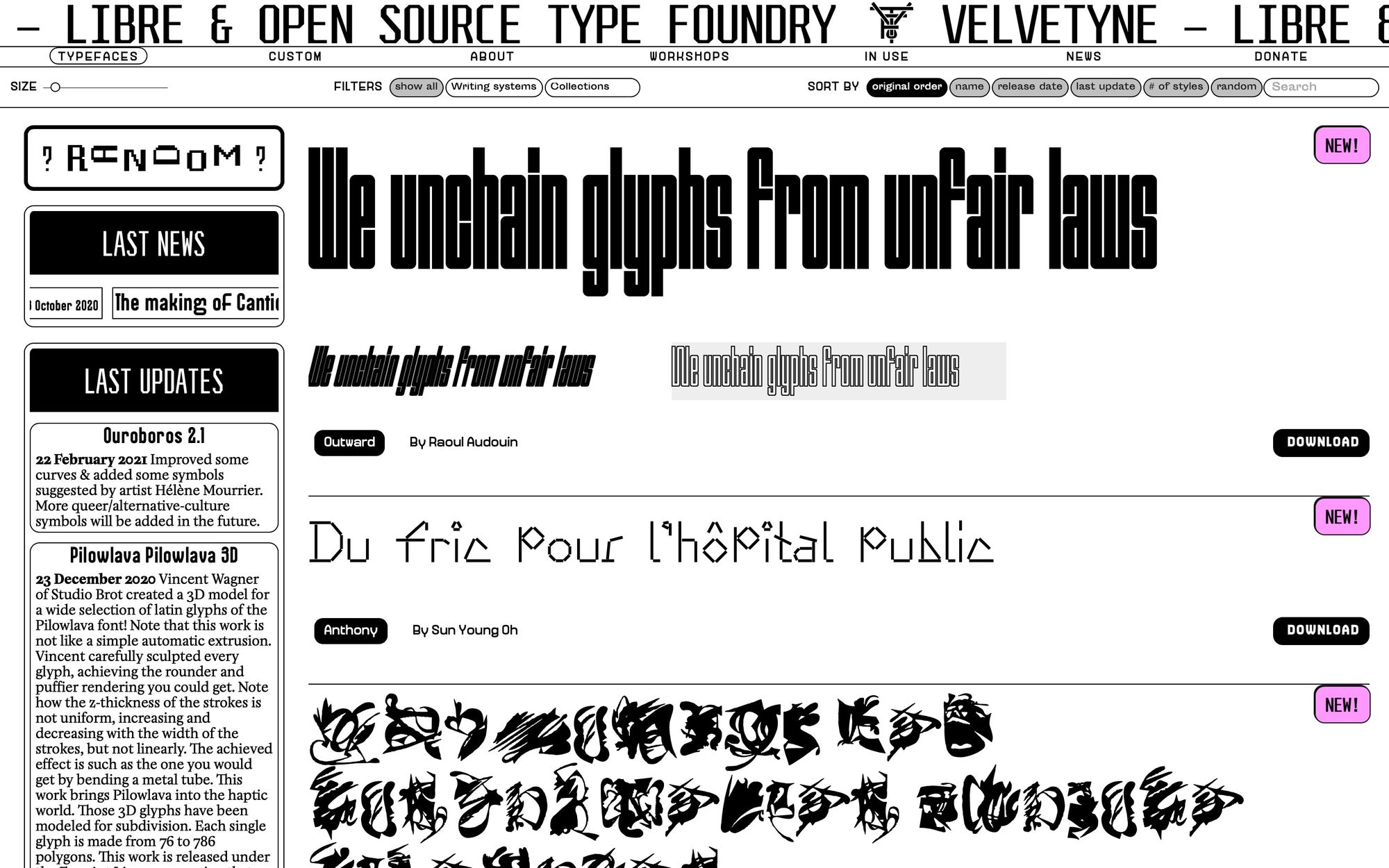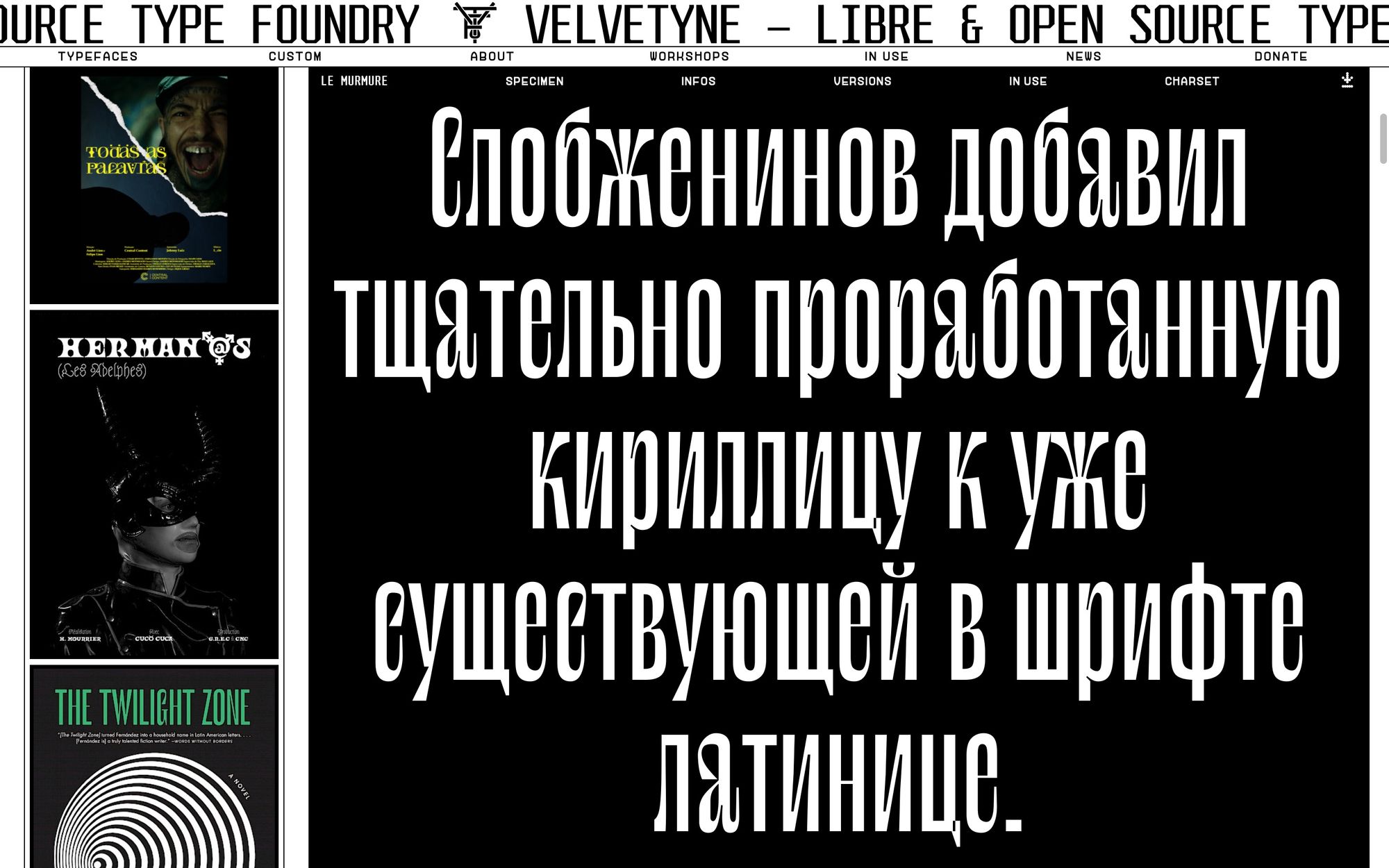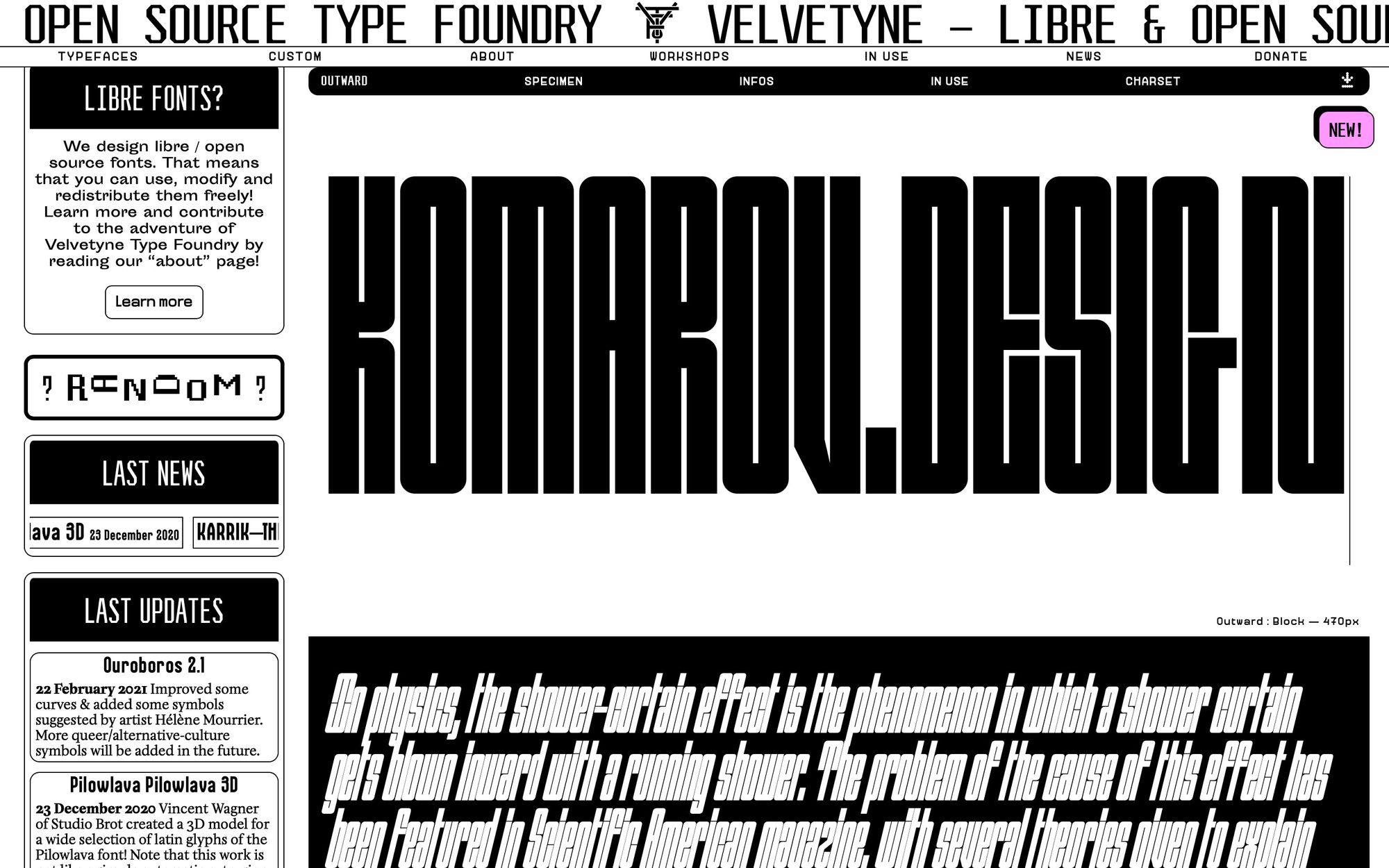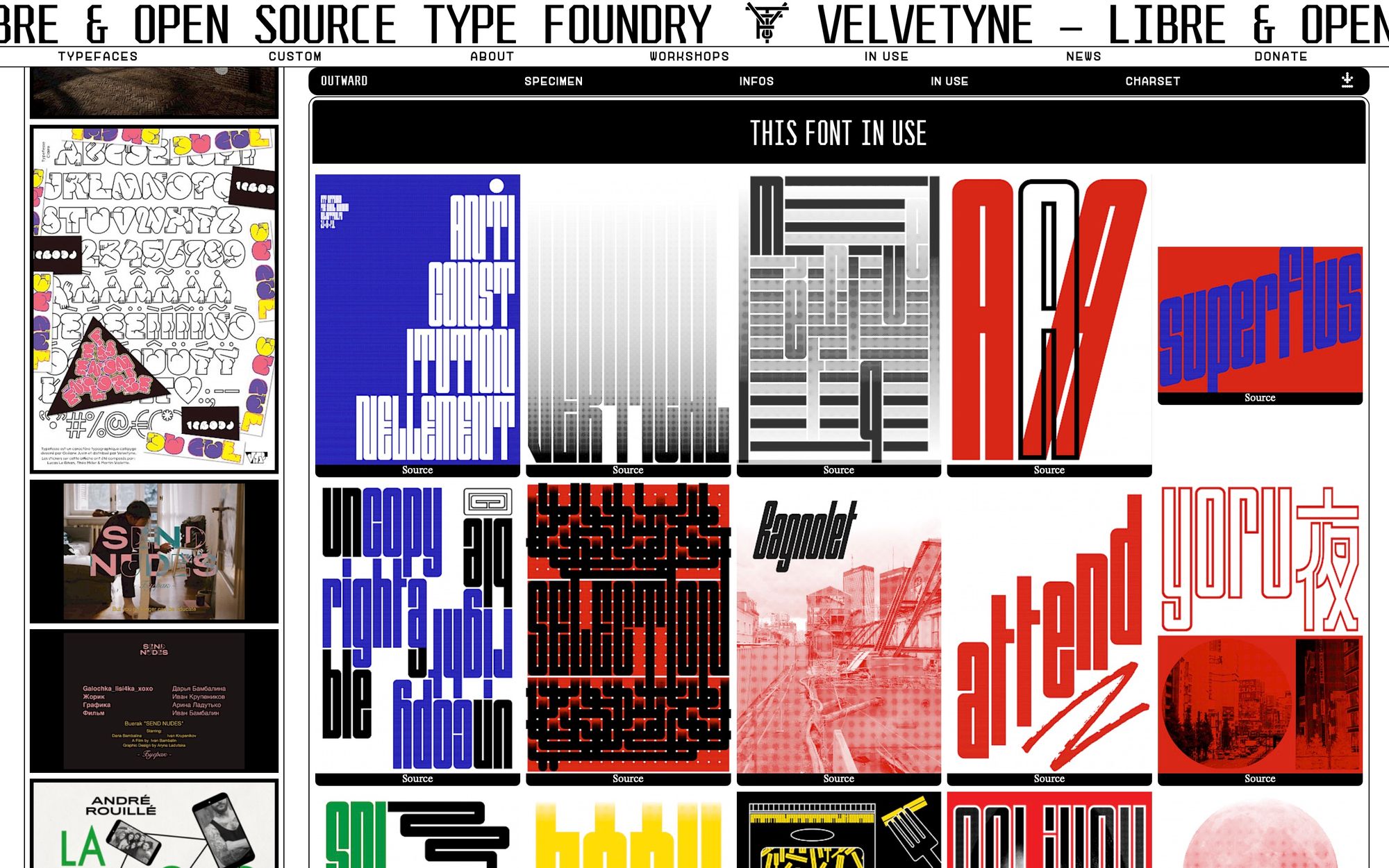
Velvetyne.fr - бесплатные шрифты для брутализма и неординарных проектов
Velvetyne.fr - это бесплатная библиотека шрифтов с отрытым кодом от независимых авторов. Идеально подойдет для дизайна в стиле "брутализм" и других неординарных и необычных проектов.
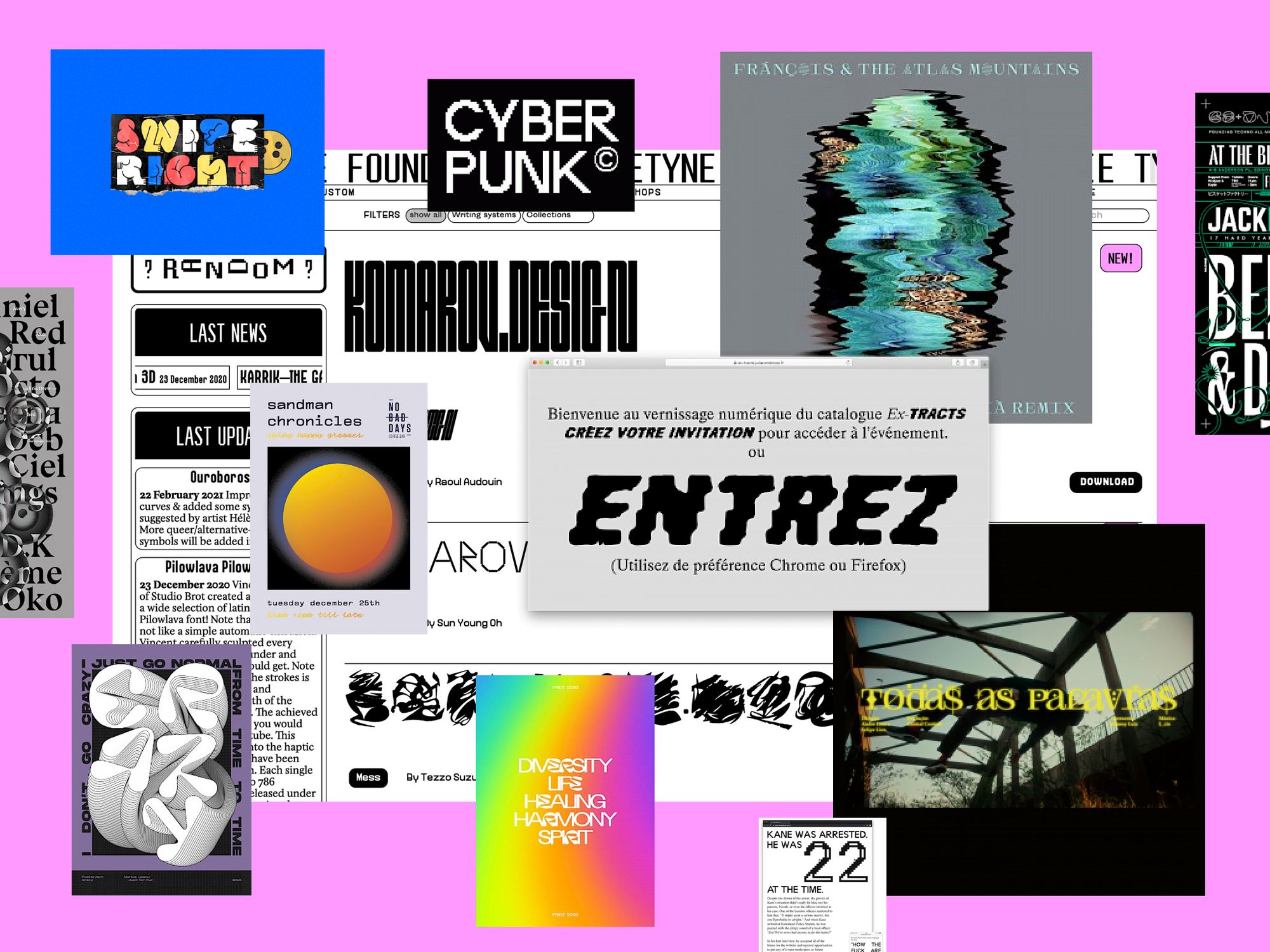
Velvetyne.fr - это бесплатная библиотека шрифтов с отрытым кодом от независимых авторов. Идеально подойдет для дизайна в стиле брутализм и других неординарных и необычных проектов. Среди шрифтов можно найти много кириллических шрифтов.
VTF был создан в 2010 году Фрэнком Адебайе как логическое продолжение его блога о типографике и шрифтовом дизайне. Он начал это сам, но тут же пригласил других любителей шрифтов присоединиться к нему в его приключении. Так родился коллектив Velvetyne, который с годами вырос до приличного числа из 10 храбрых волшебников глифов. Узнайте больше о людях стоящих за Velvetyne, на странице «Команда» .
Почему шрифты с открытым исходным кодом.
От авторов:
- Мы считаем, что проприетарные шрифты не являются лучшими инструментами для определенных творческих практик, и считаем, что эти оригинальные цели заслуживают высококачественных шрифтов. Мы считаем, что не все графические или типографские творения должны быть частью рыночной экономики, и поддерживаем свободу ниспровергать ее правила.
- Мы считаем, что SIL Open Font License (OFL) является хорошей основой для обучения людей созданию и распространению шрифтов. Мы хотим популяризировать типографику и дизайн шрифтов и сделать их более доступными для широкой публики, чтобы каждый мог понять, как они работают.
- Мы считаем, что создание более открытого и прозрачного шрифтового дизайна увеличивает динамизм современного творчества. В этом смысле пользователи могут продолжать разрабатывать и адаптировать наши шрифты в соответствии со своей точкой зрения и конкретными потребностями.
- Мы хотим превратить Velvetyne в шикарную площадку для типовых проектов, которые могут иметь низкую коммерческую привлекательность, но обладают высокой поэтической, эстетической или технической ценностью. Мы хотим поощрять и развивать эти современные творения на периферии основной типовой сцены.